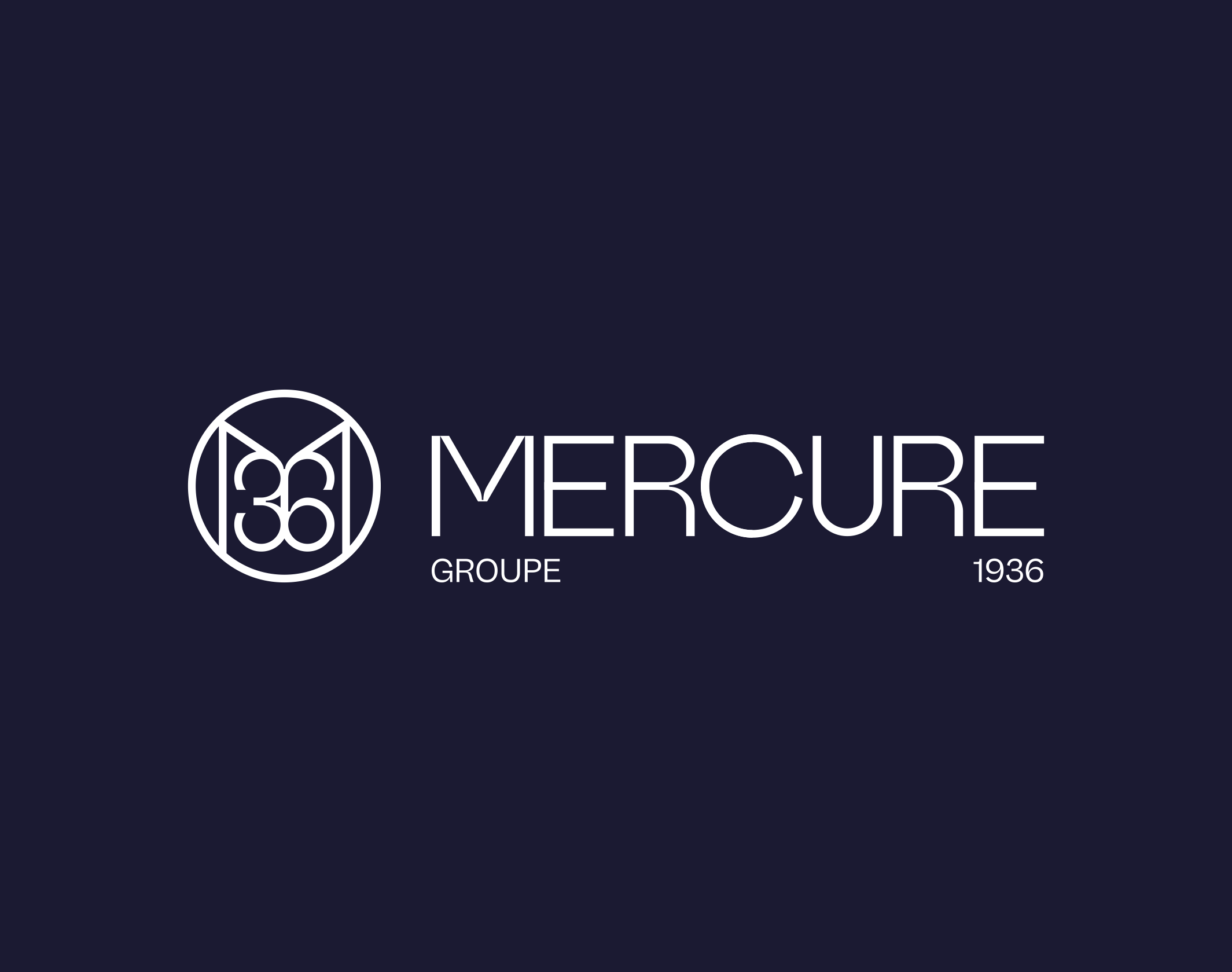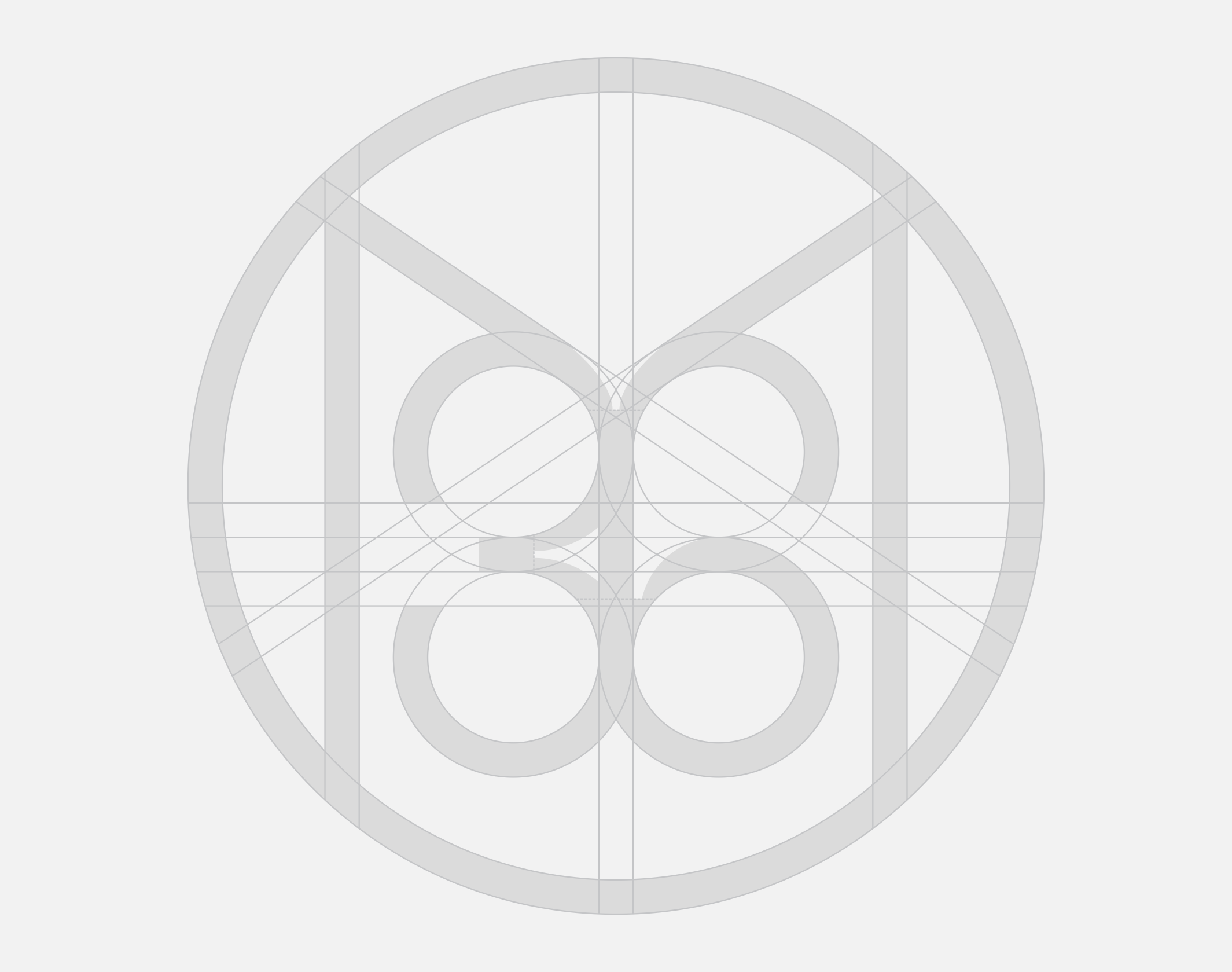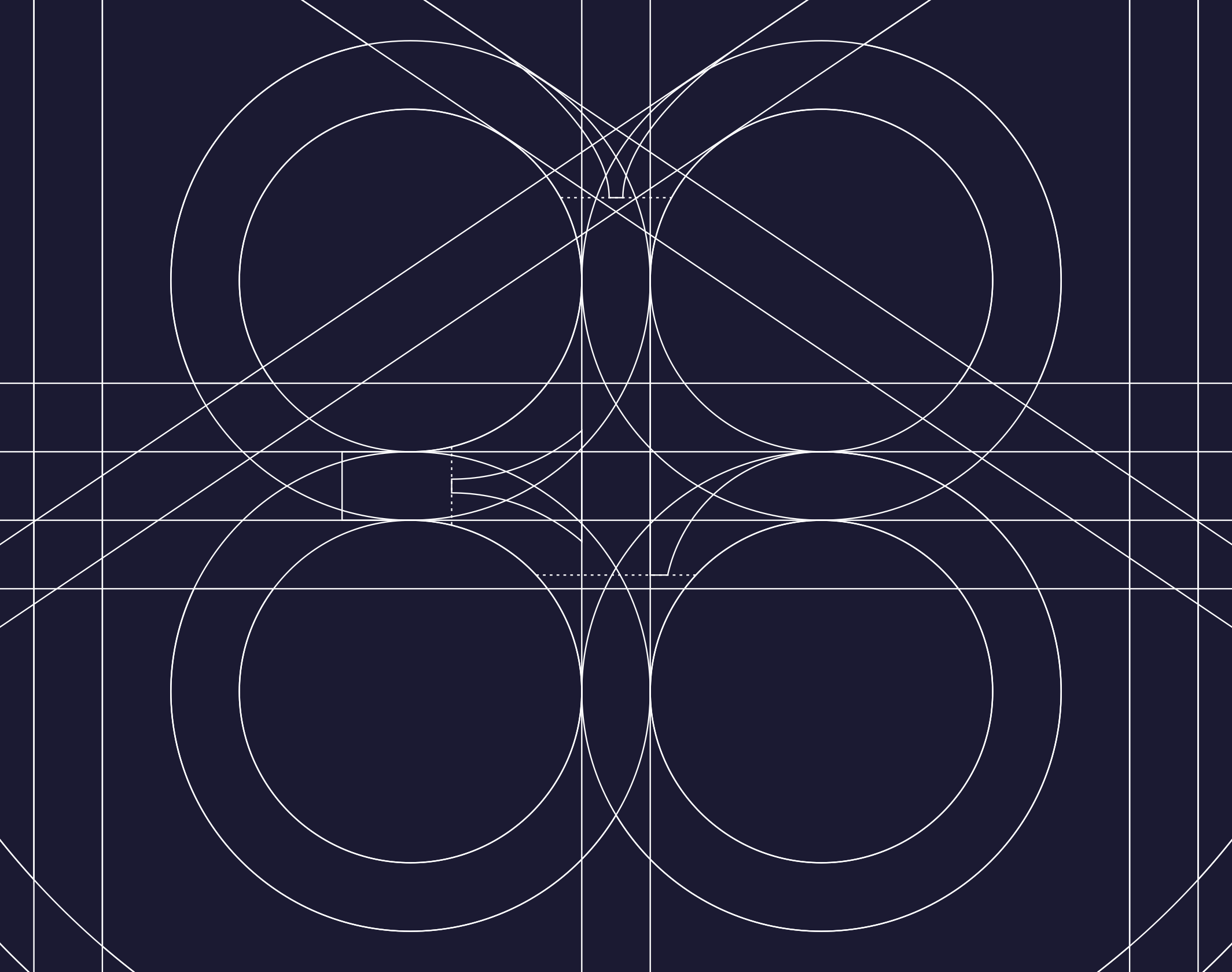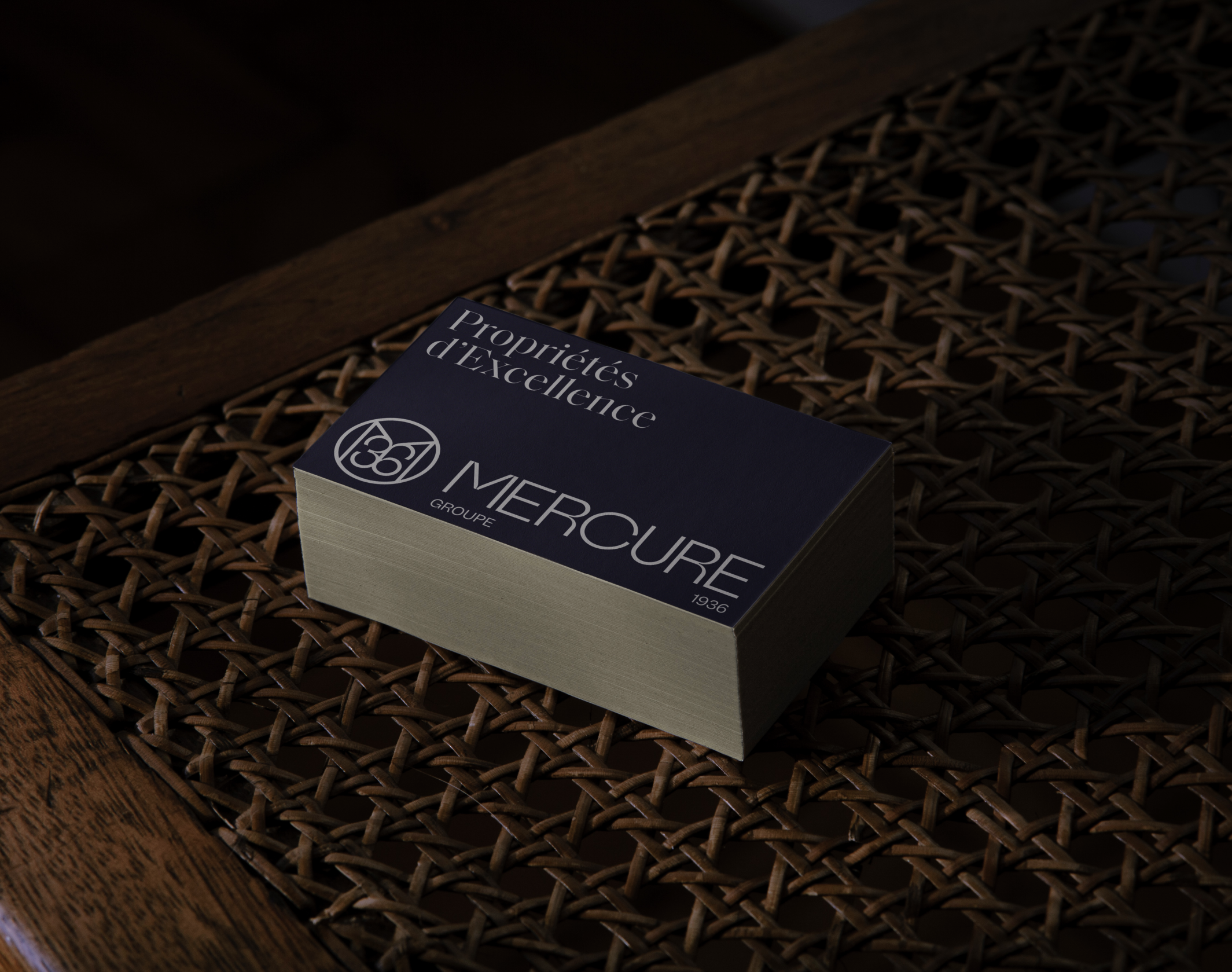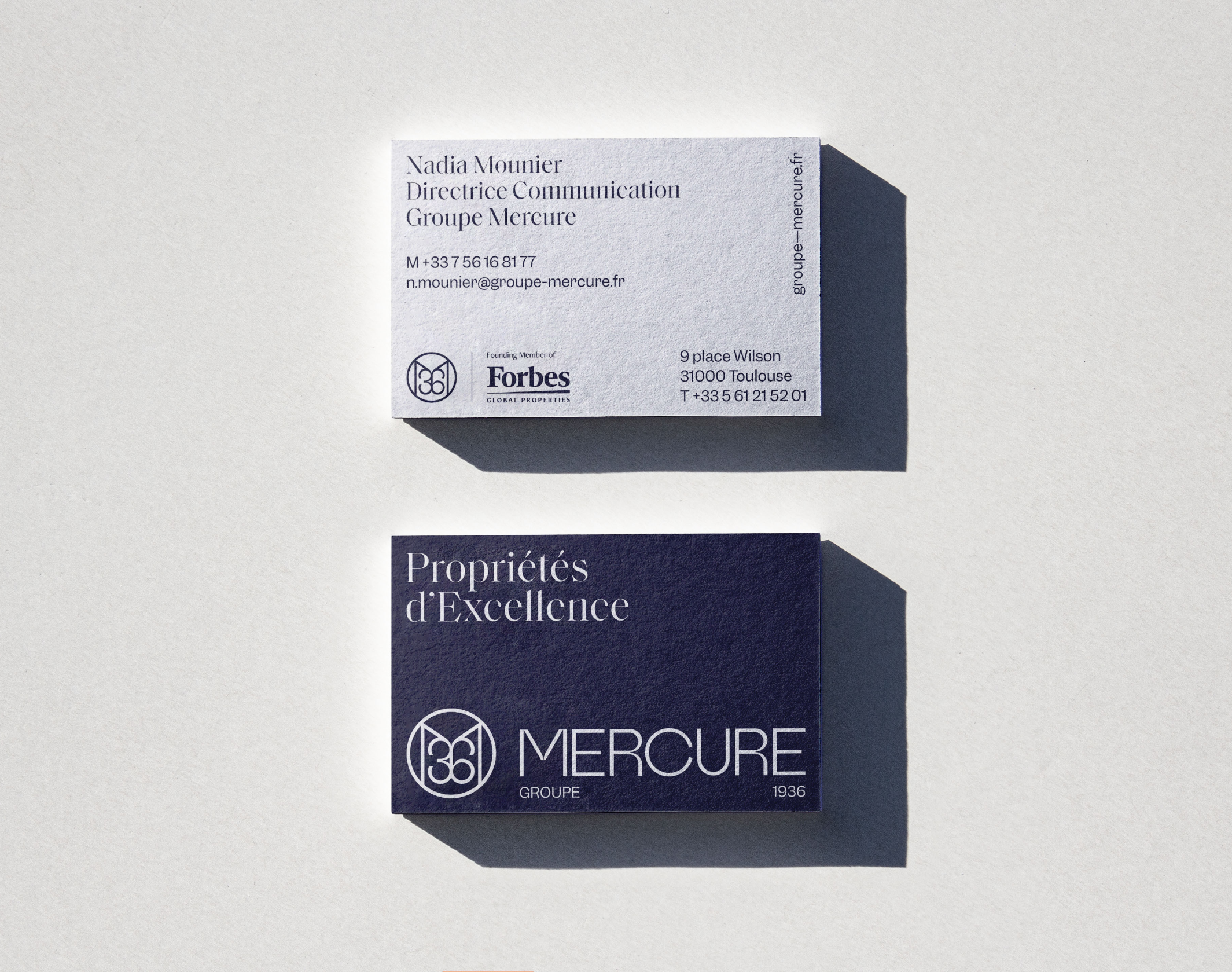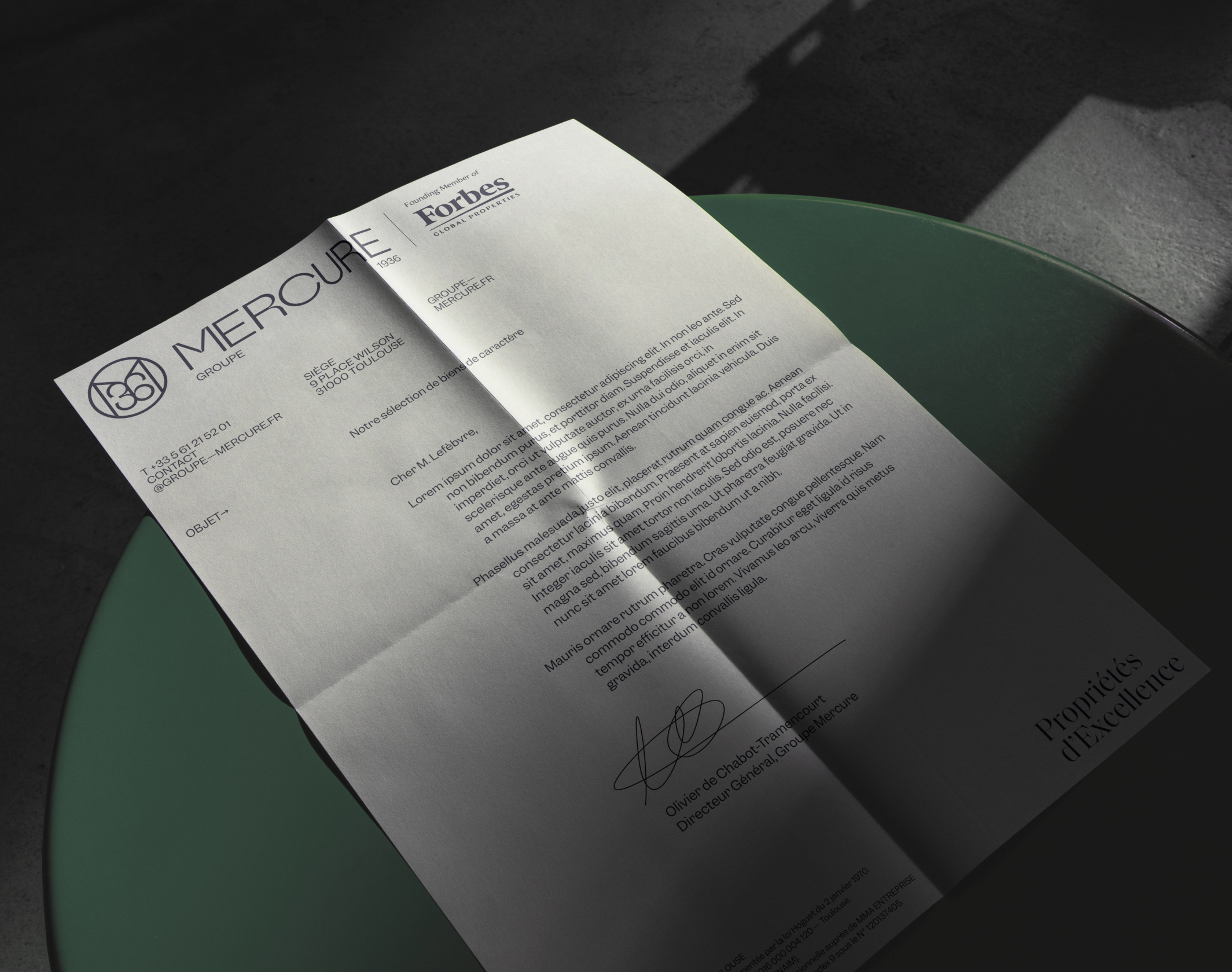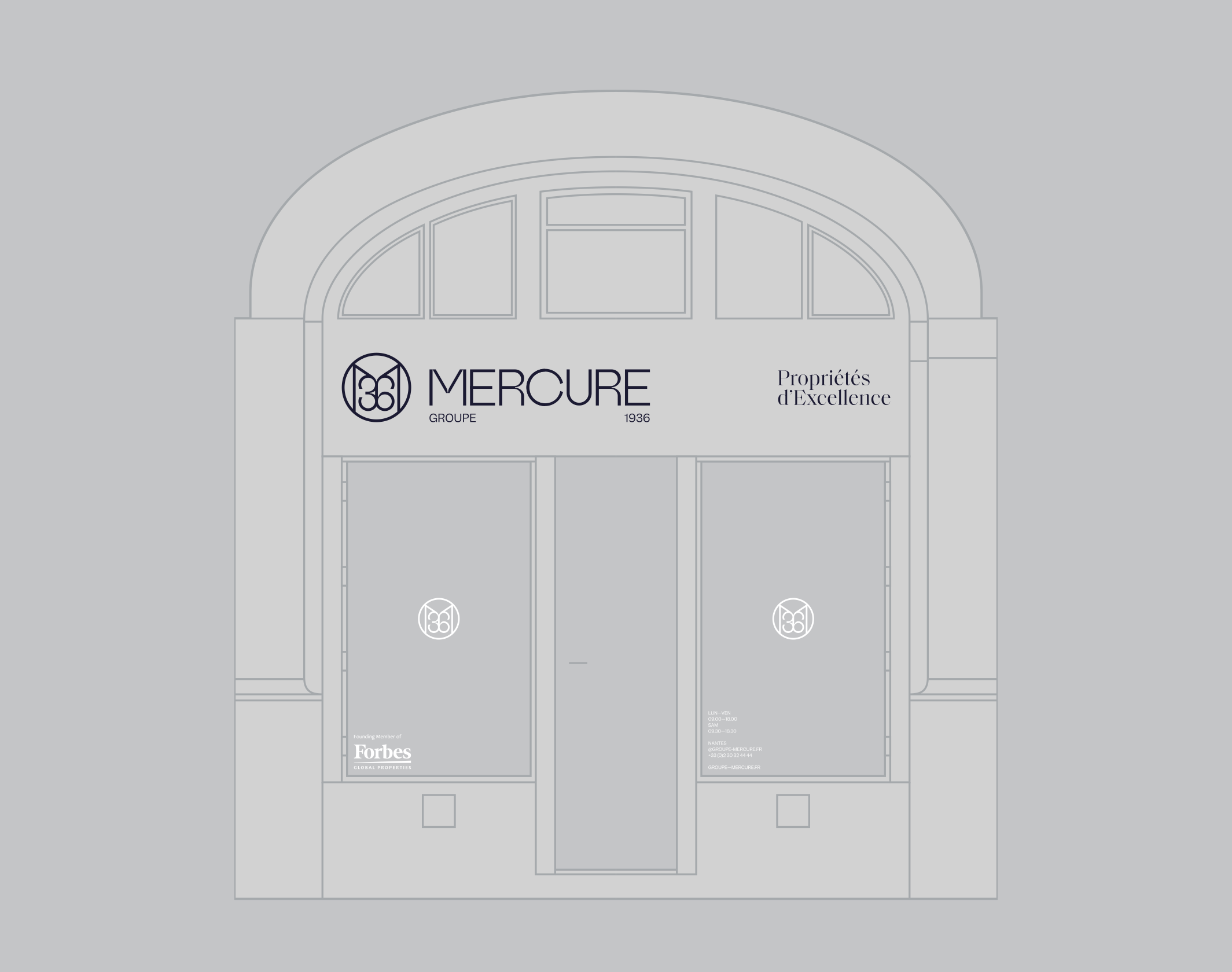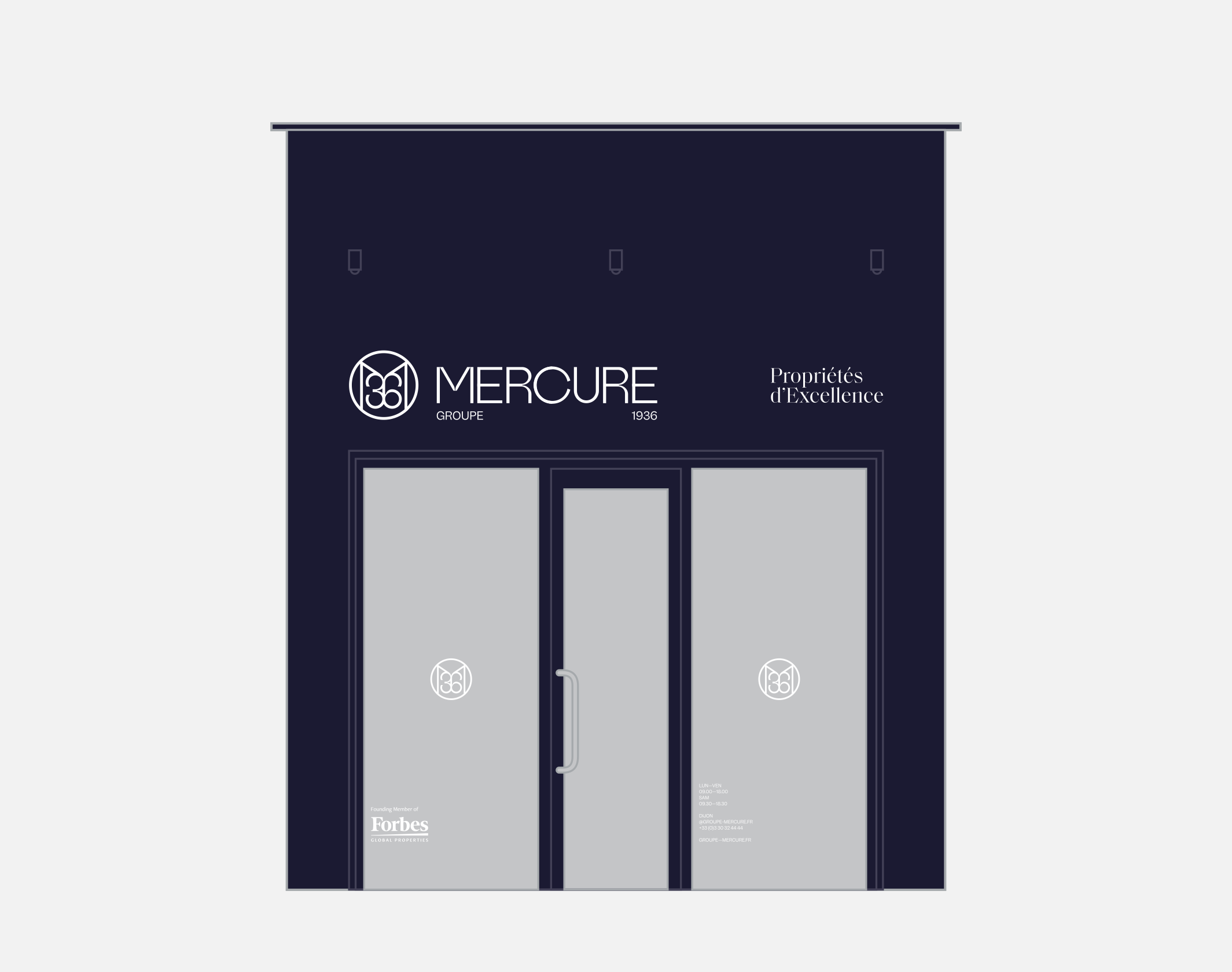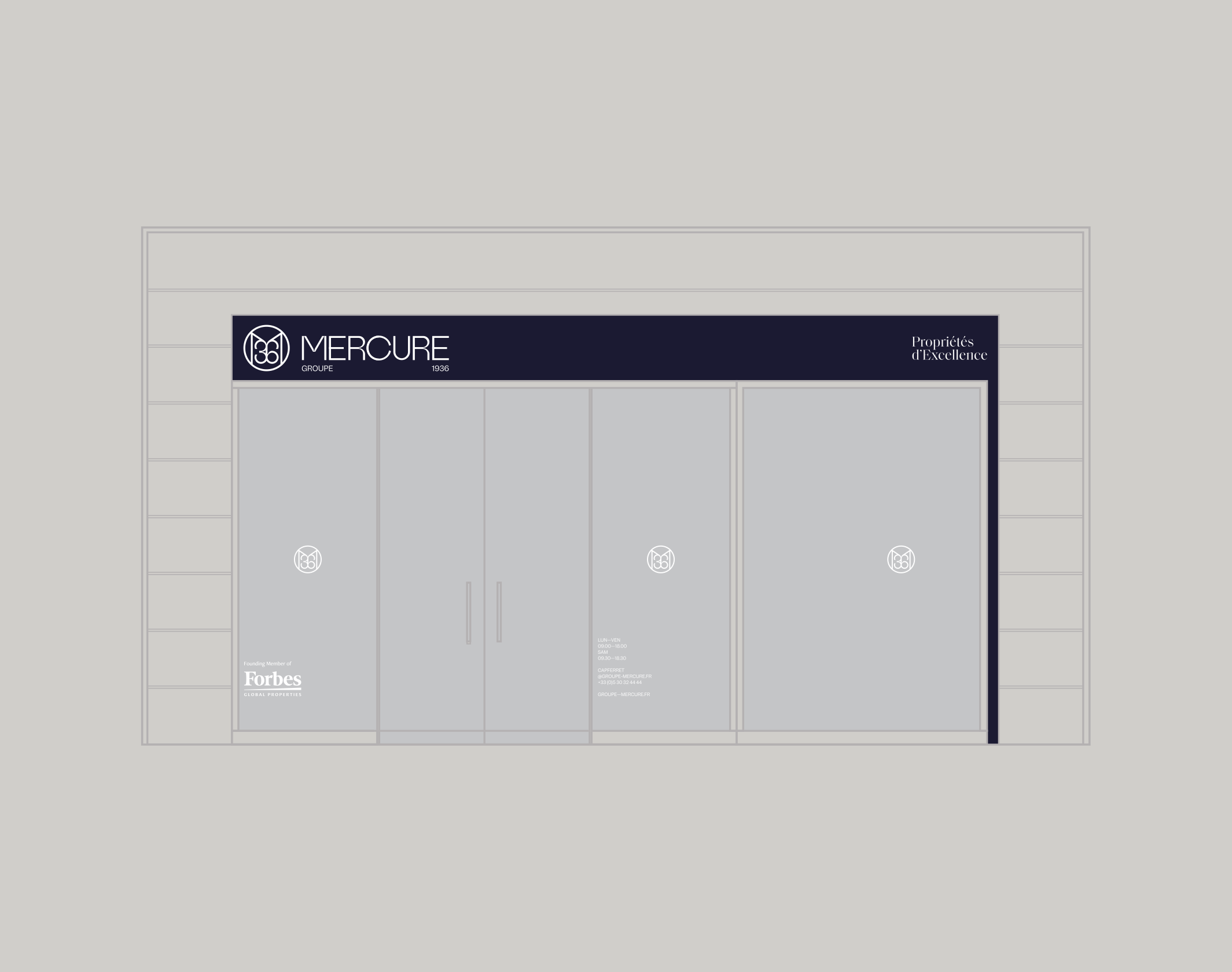
Groupe Mercure
Le Groupe Mercure a modernisé son identité visuelle pour allier héritage et élégance, affirmant ainsi son leadership sur le marché immobilier de luxe.
Le Groupe Mercure – Forbes Global Properties a été créé en 1936 et se situe dans le top 4 français des réseaux immobiliers dédiés au marché du luxe, avec plus de 2000 biens de caractère à la vente de 20 agences réparties sur le territoire. C’est aussi le leader incontesté sur le marché de niche de la vente de châteaux, en concentrant plus de 80% du parc français. Au printemps 2021, la direction du groupe a demandé à notre studio de repenser intégralement l’identité graphique de la marque, ainsi que sa signature et son système visuel.
L’héritage traditionnel de la marque et le milieu dans lequel ses équipes obligent à naviguer dans un environnement très codifié. En parallèle, notre volonté – tout comme celle des dirigeants – était d’emmener le Groupe Mercure vers des standards graphiques qui lui permettrait d’être remarqué et d’imposer un style sur le long terme. Ainsi, le nouveau logo se compose d’un lettrage maison, fin et structuré, doté de subtilités optiques qui réhaussent son élégance naturelle. Il est complété d’un monogramme « M36 » dont les caractères forment un entrelac symétrique qui évoque le raffinement à la française ou un portail en fer forgé. Cette approche singulière permet d’ancrer au coeur de l’identité graphique la longévité de la marque. Nous avons développé par la suite l’ensemble de l’environnement visuel du groupe, de sa signature (« Propriétés d’Excellence ») aux normes graphiques complètes, en passant par le design du magazine annuel. Le dévoilement du nouveau branding à eu lieu à Paris en octobre 2021, au Salon du Patrimoine.